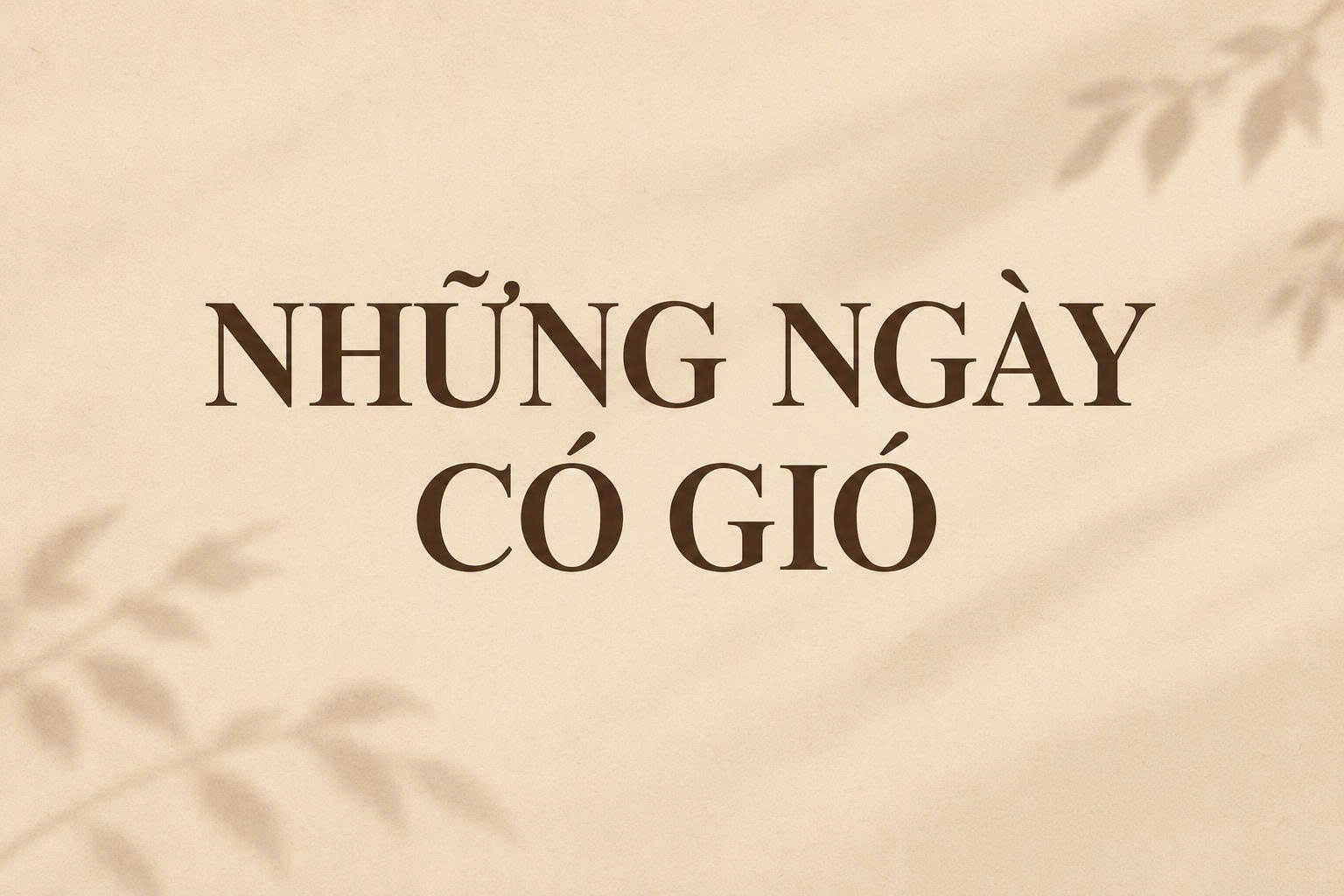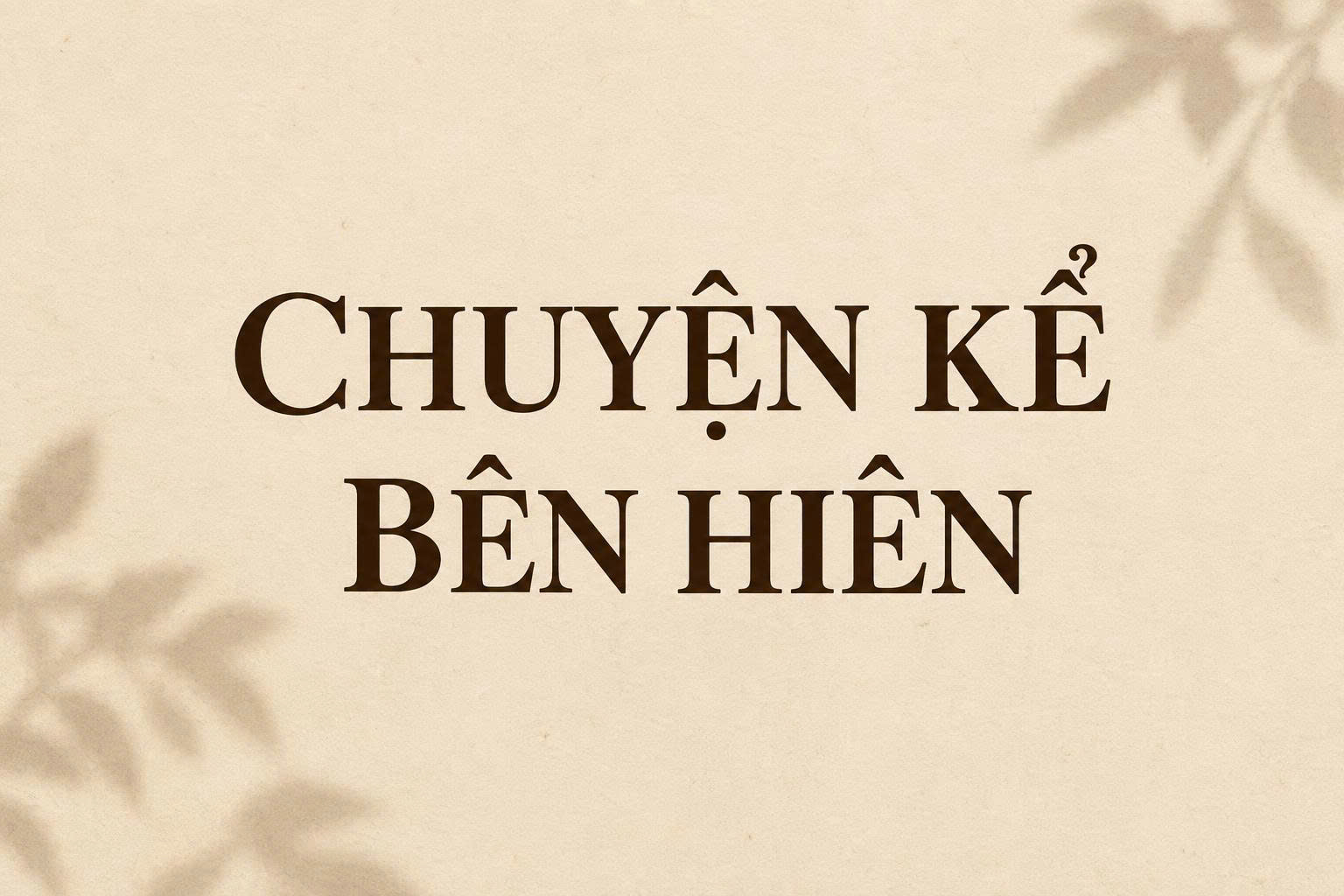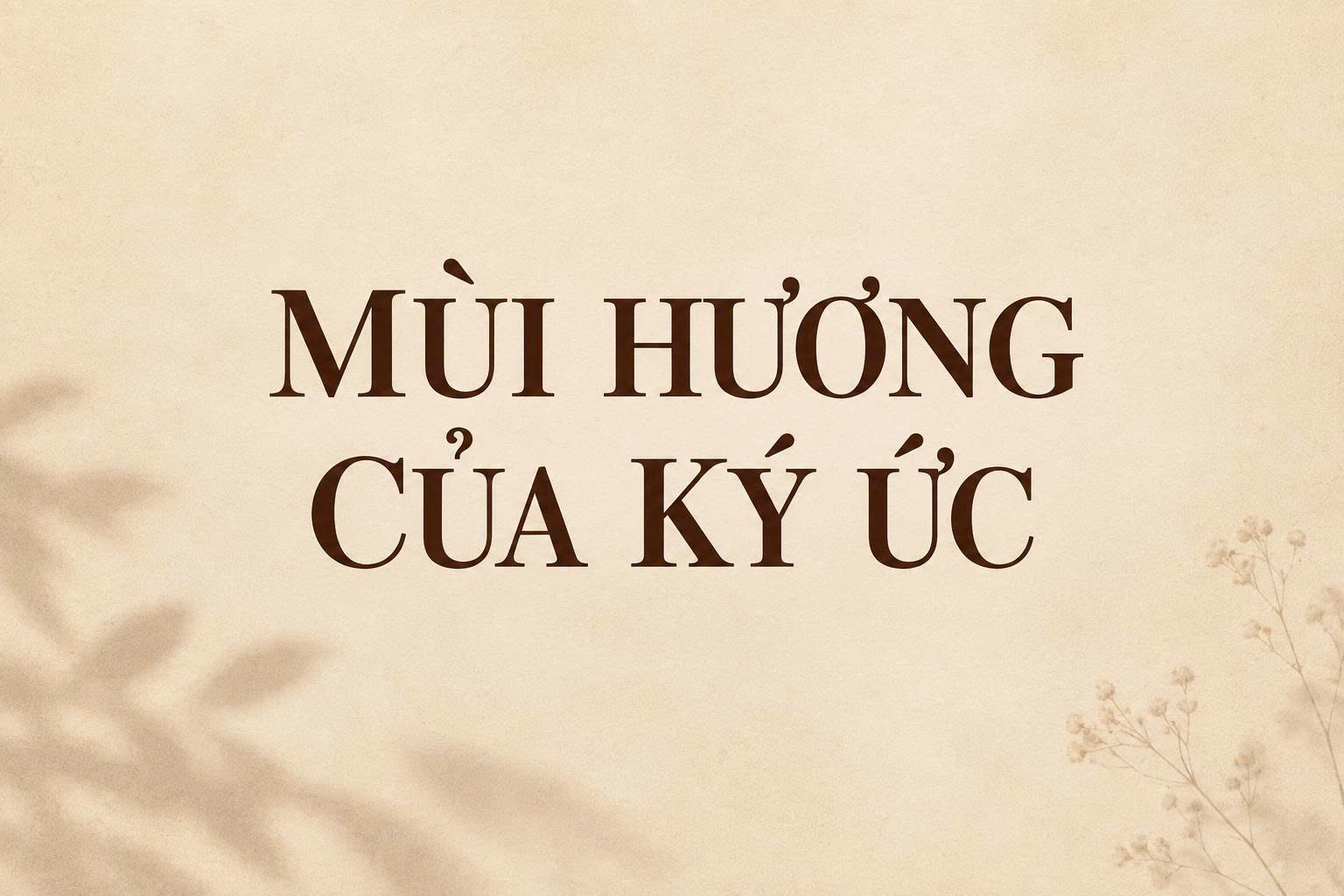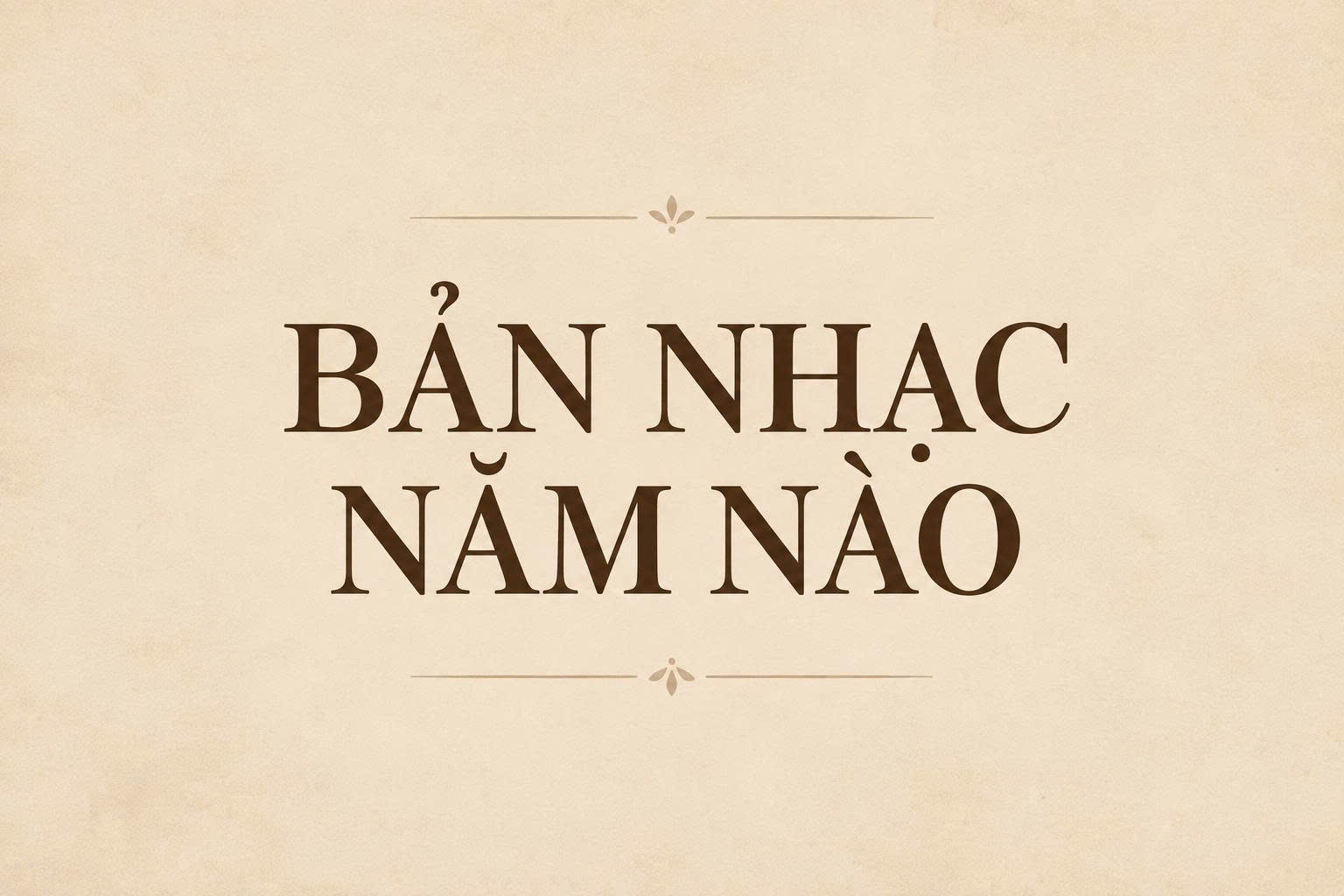
Download font VNI-Times là nhu cầu phổ biến của các designer và nhân viên văn phòng khi cần xử lý các tài liệu cũ hoặc thiết kế các ấn phẩm in ấn mang phong cách truyền thống, trang trọng. Khác với phông chữ Times New Roman sử dụng bảng mã Unicode phổ biến, VNI-Times sử dụng bảng mã VNI-Windows – một tiêu chuẩn gõ tiếng Việt kinh điển của những thập niên trước. Doozypack.vn chia sẻ link tải font VNI-Times chuẩn, giúp bạn mở file không bị lỗi chữ và tự tin dàn trang bao bì, hồ sơ năng lực chuyên nghiệp nhất.
Đặc điểm thẩm mỹ của font VNI-Times trong thiết kế
VNI-Times không chỉ là một phông chữ hệ thống; nó mang trong mình sự chuẩn mực và uy tín đặc trưng của dòng Serif (phông chữ có chân).
Mẫu chữ tiếng Việt phổ biến
Phong cách cổ điển và trang trọng
Đặc trưng lớn nhất của font VNI-Times là cấu trúc chữ có chân sắc sảo, độ tương phản nét thanh đậm vừa phải, tạo cảm giác vô cùng vững chãi và nghiêm túc. Phông chữ này gợi nhắc đến các trang báo in truyền thống, các văn bản quy phạm pháp luật và hồ sơ doanh nghiệp lâu đời. Chính vì vậy, VNI-Times là lựa chọn hàng đầu cho các thiết kế cần khẳng định sự uy tín và tính chuyên môn cao.
Độ dễ đọc tuyệt vời trong in ấn văn bản
Nhờ cấu trúc Serif được tính toán tỉ mỉ, VNI-Times giúp dẫn dắt mắt người đọc trôi chảy dọc theo dòng văn bản, giảm thiểu tình trạng mỏi mắt khi theo dõi nội dung dài. Khi được sử dụng trong thiết kế bao bì tại Doozypack.vn, phông chữ này duy trì được độ rõ nét đáng kinh ngạc ngay cả khi in trên các bề mặt giấy có vân nhám hoặc giấy Kraft.
Kiểu chữ serif dễ đọc
03 Ứng dụng của font VNI-Times trong sản xuất bao bì
Vẻ ngoài chuẩn mực của VNI-Times mang lại hiệu quả thị giác đặc biệt trên các ấn phẩm thực tế do Doozypack.vn sản xuất:
• Bao bì Dược phẩm & Thực phẩm chức năng: Nét chữ trang trọng gợi cảm giác an tâm và uy tín về chất lượng sản phẩm.
• Hồ sơ năng lực công ty (Profile): Dùng VNI-Times cho phần nội dung chi tiết giúp cuốn Profile trông bài bản và chuyên nghiệp hơn.
• Hộp giấy quà tặng doanh nghiệp: Tên công ty in bằng VNI-Times Bold kết hợp ép kim bạc tạo nên diện mạo vô cùng lịch sự.
Thiết kế văn bản tiếng Việt
03 Lưu ý kỹ thuật khi sử dụng font VNI-Times cho in ấn thực tế
Sản xuất bao bì sử dụng phông chữ đặc thù như VNI-Times đòi hỏi designer cần lưu ý một số vấn đề tại xưởng in chuyên nghiệp:
• Kiểm soát độ dày chân chữ (Serif): Các nét chân của VNI-Times khá mảnh. Trên chất liệu giấy thô nhám như giấy Kraft, bạn nên để size chữ tối thiểu từ 7pt trở lên để tránh bị mất nét do độ thấm mực của giấy.